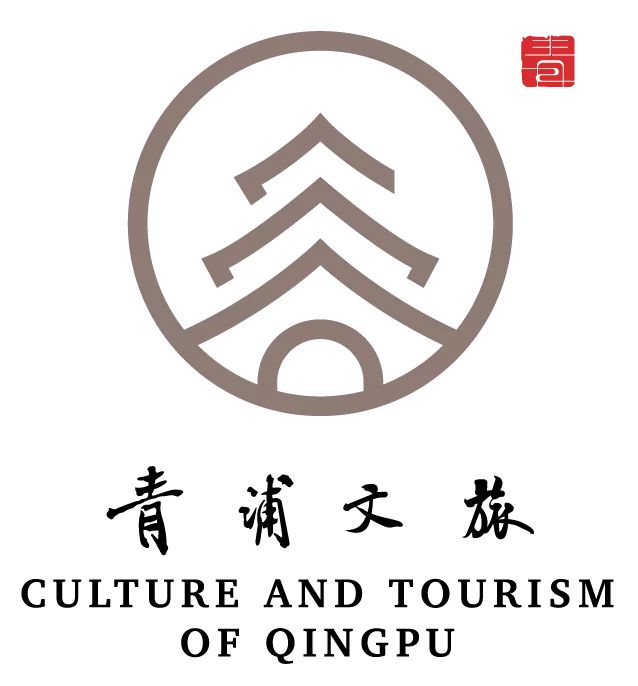
上海青浦历史悠久、文脉绵延,是底蕴深厚的上海之源。
为了更好地概括青浦文化旅游的深厚积淀与深刻内涵,展现出青浦从“上海之源”走向“上海之门”的发展历程以及新时期青浦宜居、宜游、宜业的新风貌,以更好的形象欢迎世界各地的游客来访,2022年伊始,青浦文旅全新logo重磅发布!
这个Logo创意来源于“浦”字的含义以及青浦代表性建筑放生桥,“浦”原意为江河交汇之处的滩涂。
Logo外形是浓浓的一抹笔触,恰似一片绿叶,既是滩涂的生动表现,也寓意依水而建、以水为生的青浦历史与未来;中间“五孔”,意为五浦交汇,凸显独特的江南水乡韵味。
Logo中间水墨部分似“一”字,寓意青浦敢为人先、争创一流;繁体字“善”字印章,是对“绿色青浦,上善之城”宣传主题的生动呼应。
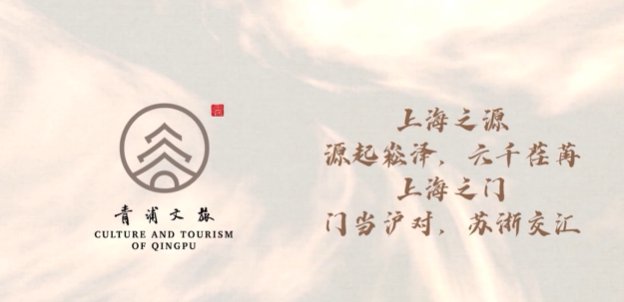
此次青浦文旅全新LOGO的设计,充分结合美学和地域特色,将崧泽文化遗址中的上海第一人、第一房、第一井、第一谷、第一村以及上海之门的概念一一叠加,形成了青龙塔的形象,暗喻青浦得名于青龙镇和五大浦。选用代表崧泽文化的陶土棕作为主色调,构成了简约形、江南韵的LOGO,诠释了“上海之源,源起崧泽,上海之门,开门迎客”的文旅理念,彰显了文化自信和旅游内涵。
6000年前在青浦,有一个“年轻人”,是迄今考古发现已知最早的上海先民,又被誉为“上海第一人”。
6000年前在青浦,有一把“稻谷”,是通过考古发掘第一次发现的有确凿地层依据的稻谷遗存,被誉为“上海第一谷”。
6000年前在青浦,有一间“房”,别看这小小的5.5平方米,掌握了房屋建筑技术的上海先民,已不再风餐露宿,心有归属。
6000年前在青浦,有一口“井”,是中国出土年代最古老的直筒形水井,表明上海是我国最先发明了找水和储水先进技术的地区。 6000年前在青浦,有一座“村落”,上海的先民们安营扎寨,比邻而居,这种环濠聚落的形态,与进入文明时代后带有护城河的城市形制一脉相承。 在青浦,还有一座始建于唐代的青龙塔,见证了海上贸易港口青龙镇的繁华风貌,迎来送往无数流连忘返的文人墨客。青浦,便得名于青龙塔、五大浦。
效果展示图: